Sie gilt – neben dem MA Typeface Design im britischen Reading – als die Königsklasse des internationalen Schriftdesigns: die einjährige Type and Media-Ausbildung an der Royal Academy of Art in Den Haag. Der Master-Kurs bietet alle Disziplinen des Type-Design an, von der Kalligrafie über das Steinhauen bis hin zur Python-Programmierung und der Schöpfung neuer Letterformen. Der international mit Spannung erwartete Höhepunkt von Type and Media ist die Veröffentlichung der Abschlussarbeiten im Juli eines jeden Jahres. Heute ist es wieder soweit: “This website is an archive of the final project typefaces created in the last four months of the 2011/2012 course. For more information, please visit the Type and Media or the KABK website.”
Genauso bunt wie die Website ist das Spektrum der Nationalitäten des Studiengangs 2011/2012. Sie kommen aus Australien, Kroatien, Deutschland, Ungarn, Island, Indien, Lettland, Mexiko, Spanien, der Schweiz, Tadschikistan und Taiwan. Gestaltung und Implementation der Site: Thijs van der Vossen von Fingertips, Text gesetzt in Nitti von Bold Monday.
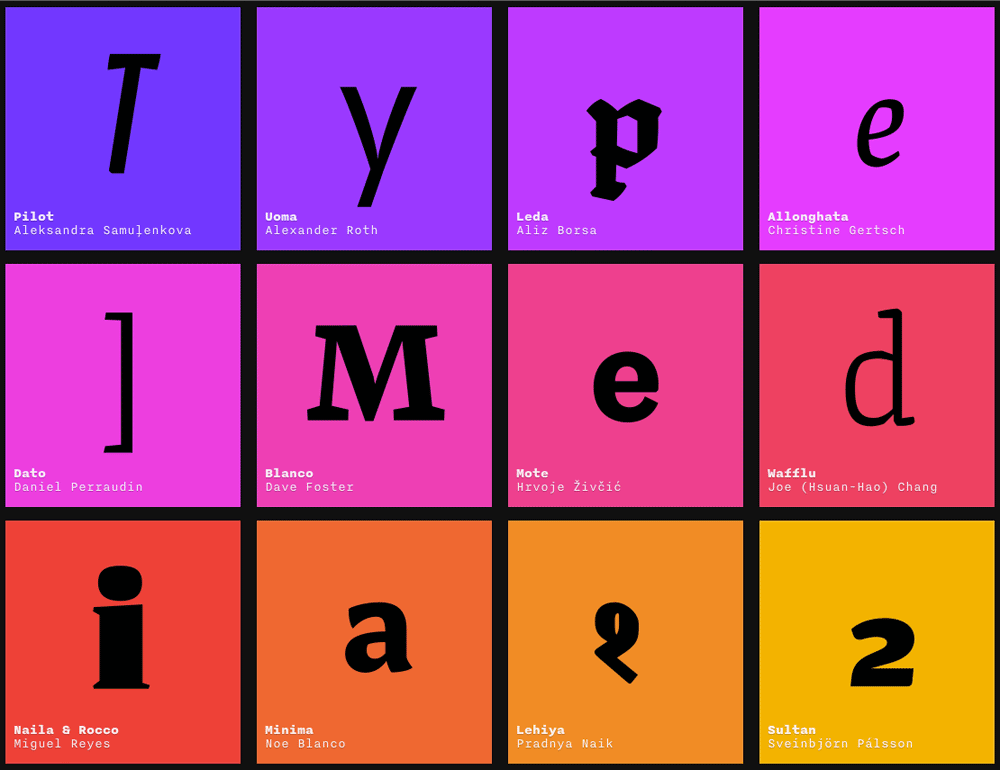
Da sind ja wieder einige Perlen dabei. Auch wenn ich das Deja-Vu-Phänomen nicht ganz leugnen kann. Stichwort Antique Olive, Haptic, Amman oder Doko.
Was passiert eigentlich mit den Entwürfen dieser Type-Media-Kurse? Werden die weiterentwickelt, so dass man irgendwann eine Lizenz erwerben kann?
Idee des Kurses ist es eigentlich nicht, fertige Schriften zu produzieren – was in dieser kurzen Zeit auch nicht möglich ist – sondern so viel wie möglich auszuprobieren und zu lernen. Dennoch arbeiten natürlich viele Absolventen und Absolventinnen an ihren Projekten weiter und veröffentlichen die Schriften, wenn sie soweit sind, selbständig oder bei einer Foundry. Du kannst auf der typemedia2012 website den Newsletter abonnieren um über die Zukunft der Projekte auf dem Laufenden gehalten zu werden.